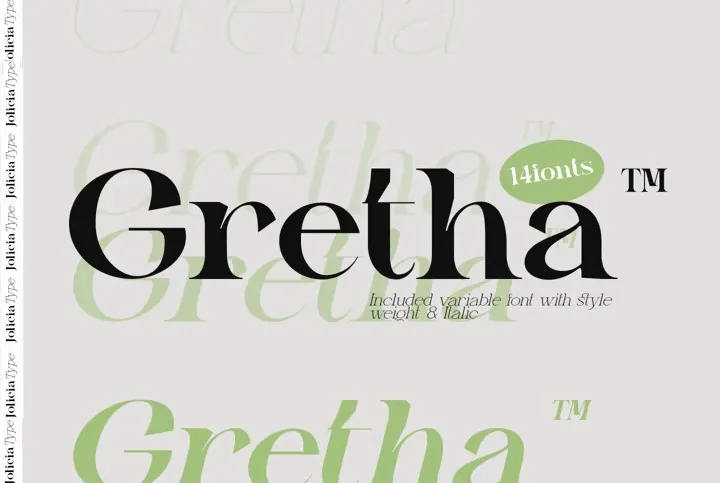
A Gretha Font é uma elegante família serif que oferece um estilo sofisticado e moderno. Criada pelo Designer Jolicia Type, esta fonte se destaca por sua forte presença visual e seu encanto atraente. A Gretha é uma fonte variável que permite ajustes de peso em várias aplicações digitais, como o Adobe Illustrator. Com as sliders variáveis presentes no design software, você pode escolher entre um conjunto de opções de peso compatíveis. Experimentar alterações individuais nos caracteres da fonte pode dar ao seu tipo uma aparência única e distintiva. Adicionalmente, esta família vem com alternativas de caracteres para oferecer ainda mais opções estilísticas. A Gretha é perfeita para quem busca um design sofisticado com elegância discreta.